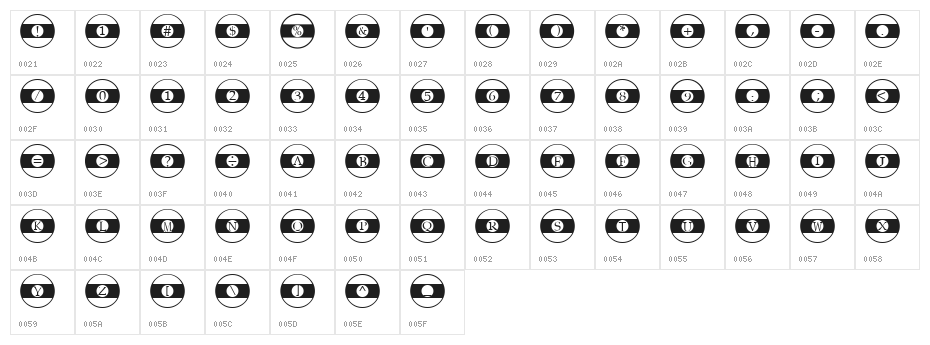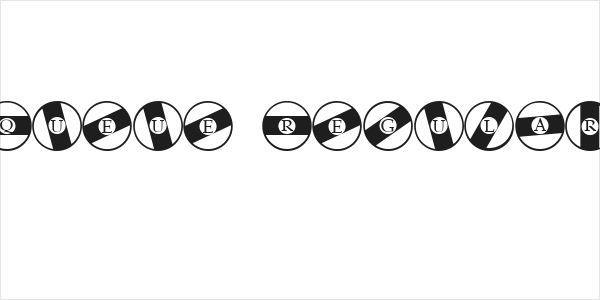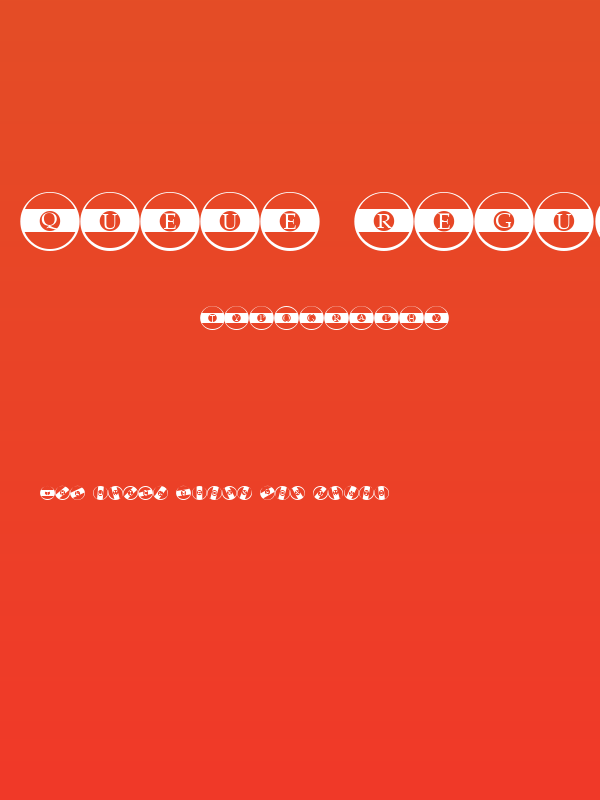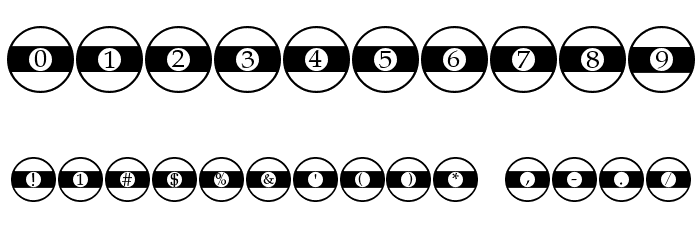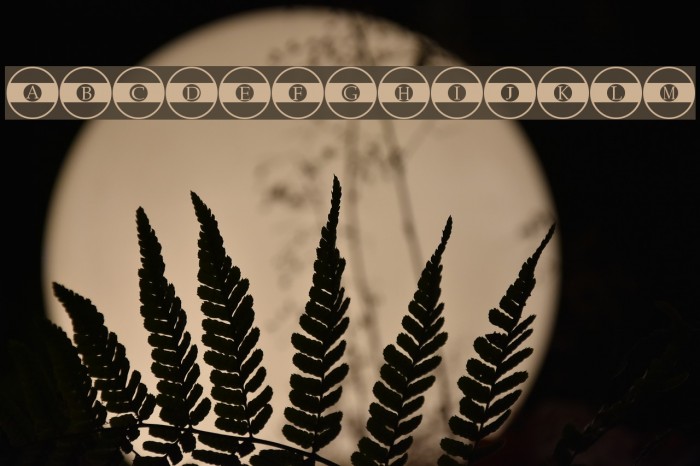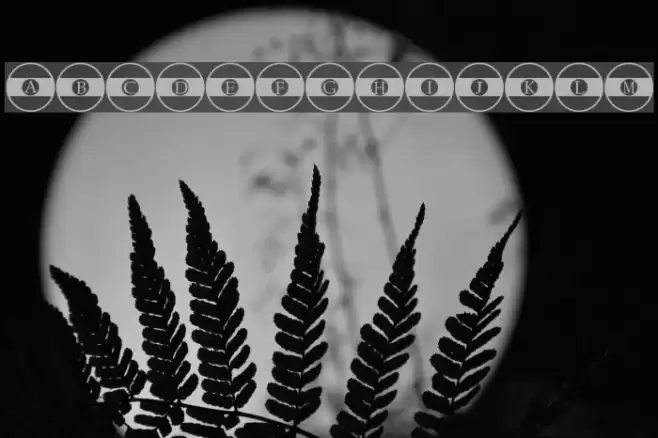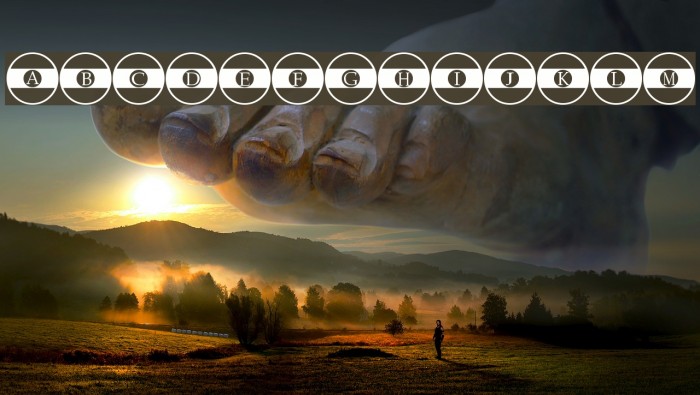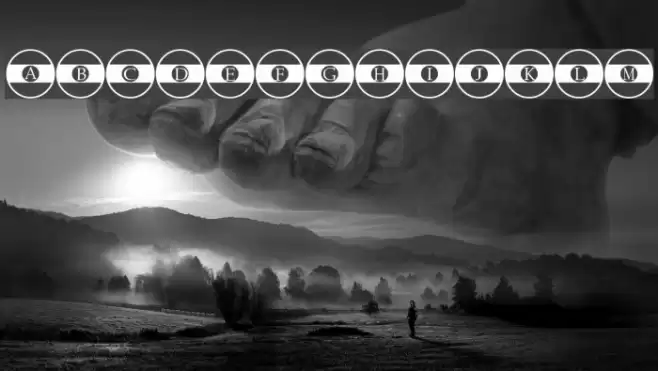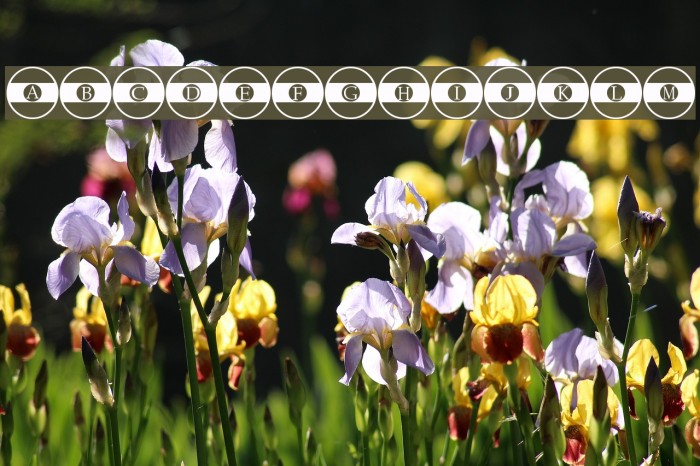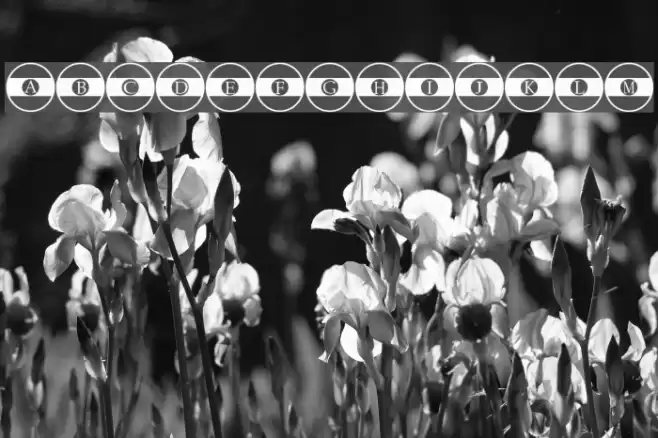
Queue Regular Font
| Stil general | Modern, Decorative |
| Caz de utilizare | Logos, Posters, Branding |
| Proiecte propuse | Ideal for branding, logos, posters, and any design project that seeks a bold and unique visual impact. |